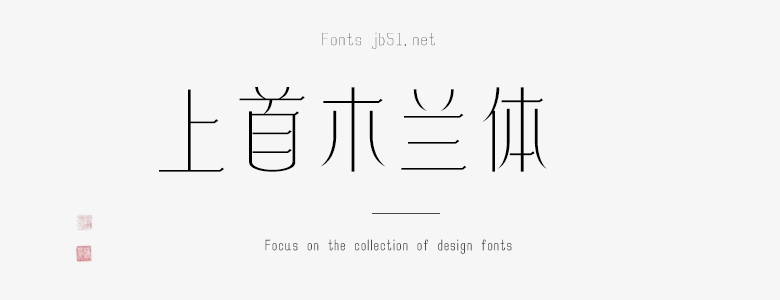
上首木蘭體是由上首造字字庫出品的字體,字體筆畫輕柔優(yōu)美但不失力量,整體字型修長,適用于搭配標(biāo)志、廣告標(biāo)語、商業(yè)廣告等高端屬性,需要的朋友可以前來本站下載。
上首木蘭體,簡體中文約6763字,字體筆畫輕柔優(yōu)美但不失力量,整體字型修長,顯得更加挺拔。風(fēng)格端莊雅致,秀潤娟美。適用于搭配標(biāo)志、廣告標(biāo)語、商業(yè)廣告等高端屬性。